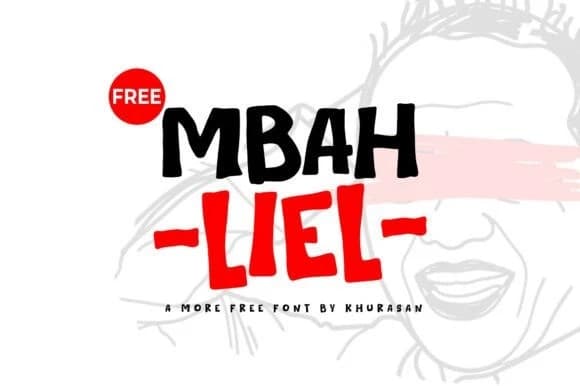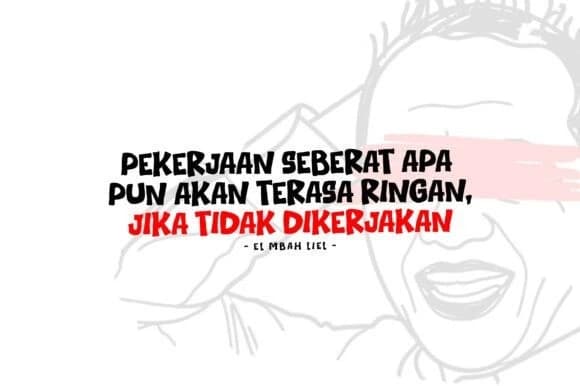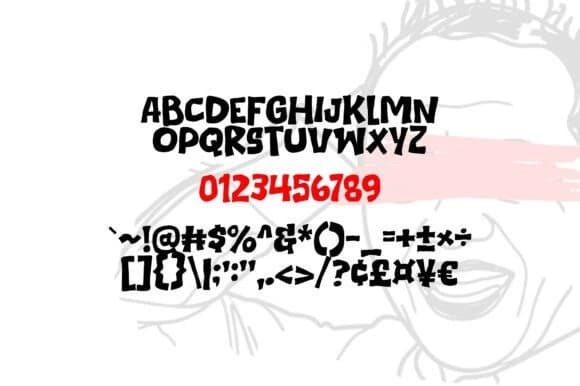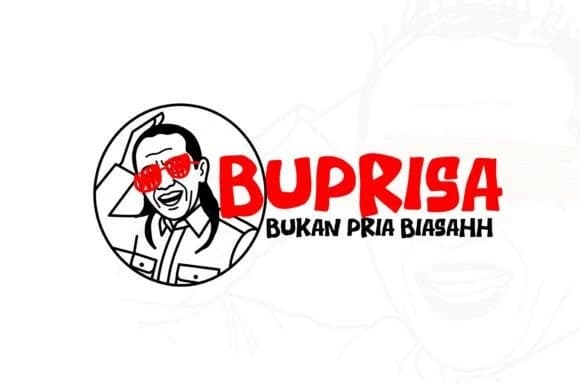
Mbah Liel Font
Mbah Liel Font - Mbah Liel ile yaratıcı projelerinize ciddi bir etki katın! Bu cesur, elle çizilmiş bir gösteri yazı tipi, etki için tasarlandı. Kalın çizgileri ve sık harf aralığıyla, yüksek sesli, enerjik ve hafif asi bir hava getiriyor—çizgi romanlar ve kentsel sokak sanatını hatırlatan.
Mbah Liel Font - Yaratıcı projelerinize ciddi bir “oomph” katın, Mbah Liel ile! Bu kalın, elle çizilmiş bir gösteri fontu etki yaratmak için tasarlandı. Kalın çizgiler ve sıkı harf aralığı ile gür, enerjik ve biraz asi bir hava getiriyor—çizgi romanlar ve kentsel sokak sanatını anımsatıyor.